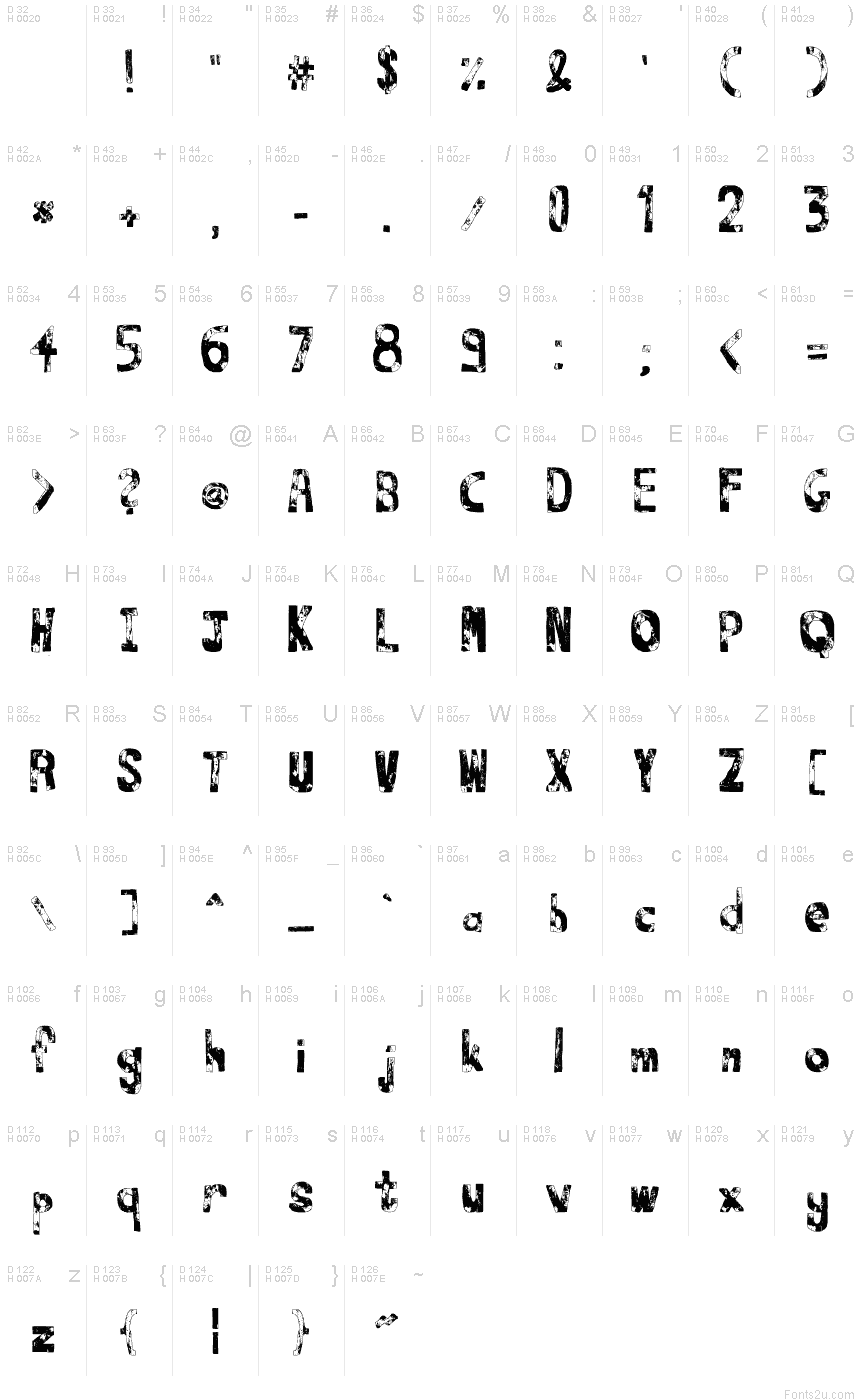
خط That's It! من Veredgf هو خط عرض (display font) مجاني بتصميم متآكل، يتميز بطابع خشن ومتهالك يوحي بأنه مختوم ومخدوش وربما متمرد قليلاً. الحروف متينة ومباشرة في بنيتها الأساسية، لكن القوام المتشقق الذي يتكرر في جميع الحروف يمنحه لمسة يدوية خشنة بعيداً عن المظهر المثالي للملصقات.
يتناسب الخط بشكل طبيعي مع المجلات (zines)، وملصقات الفرق الموسيقية، وتصاميم لوح التزلج، وأغلفة الأعمال المستقلة، والعناوين حيث يمكن لخط مجاني يتمتع بهذا القدر من التأثير أن ينجز المهمة بسرعة. وبما أن الأشكال بسيطة والقوام هو العنصر البارز، فهو يعمل بشكل جيد أيضاً للشعارات القصيرة، والملصقات، وأفكار الشعارات (logos) التي تحتاج إلى لمسة قوية وواقعية.